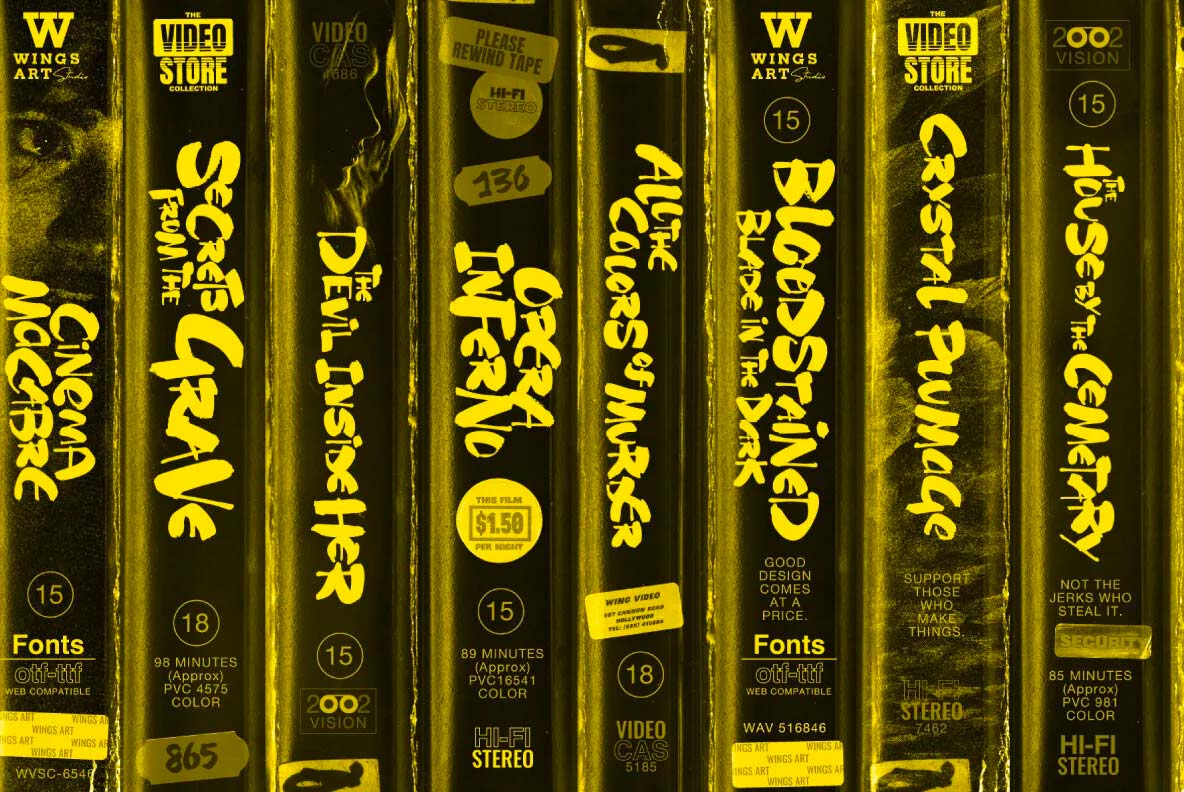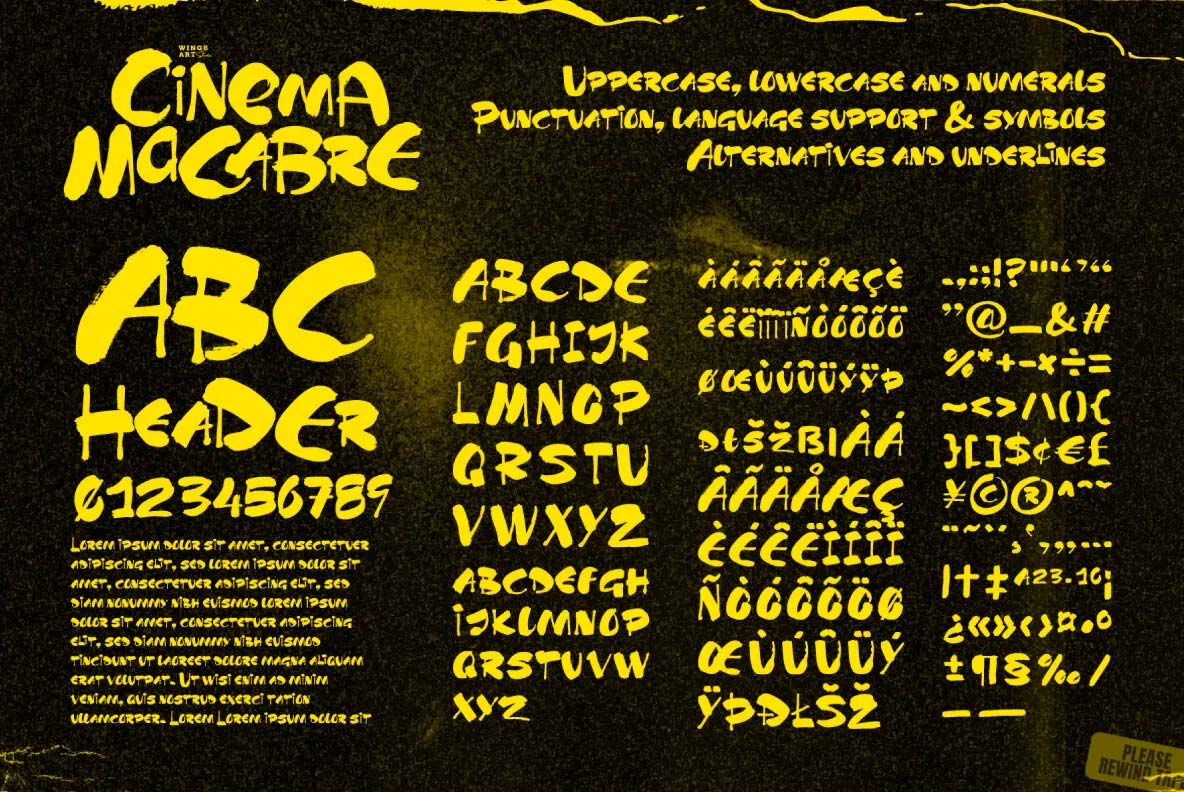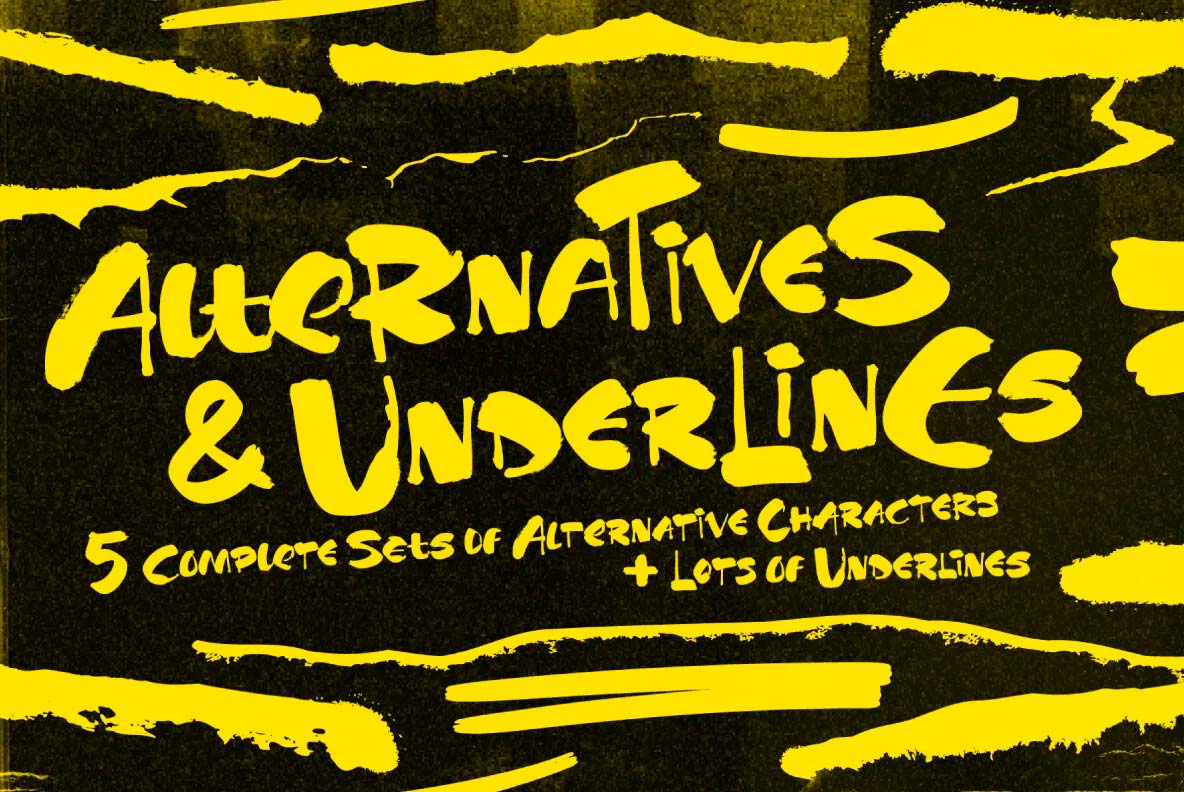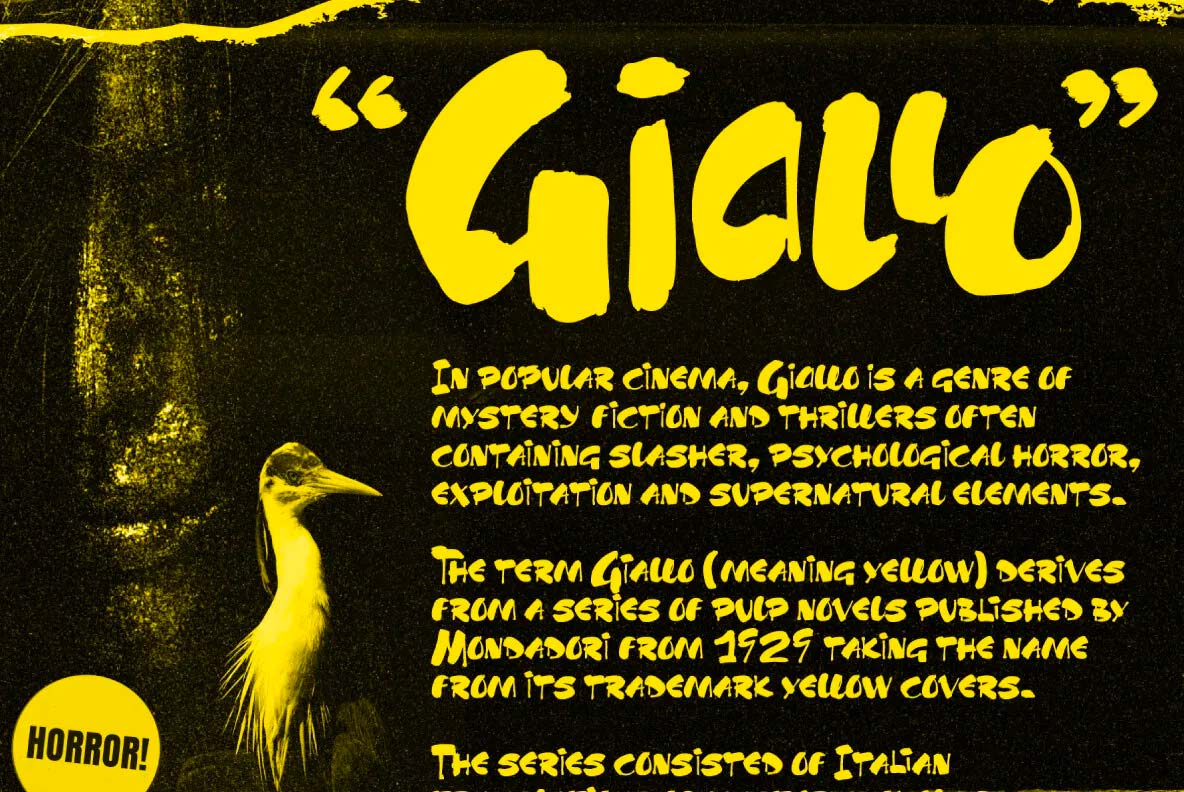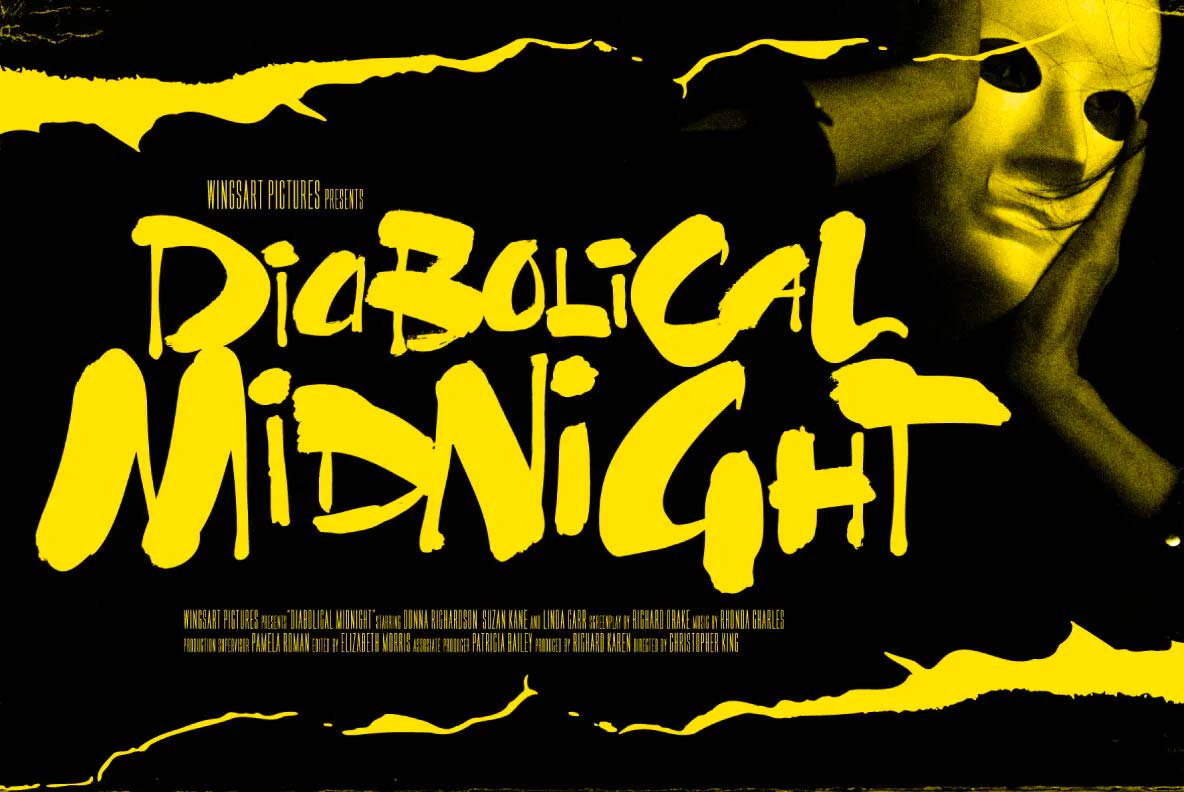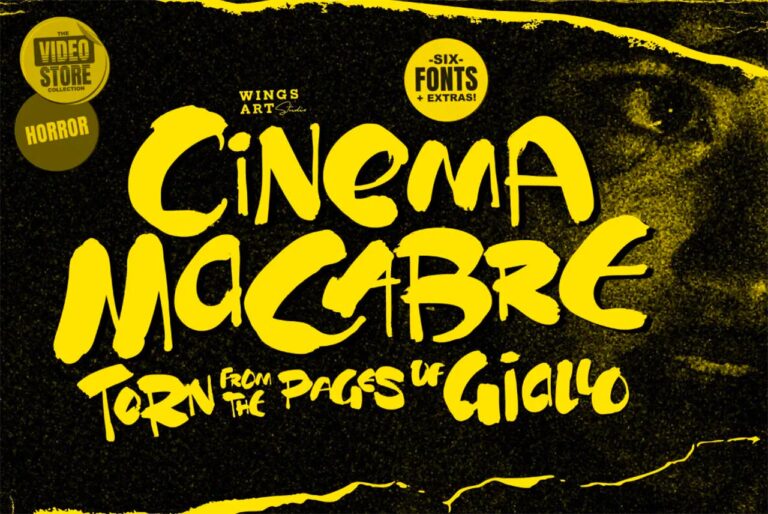
Cinema Macabre – Phông chữ hiển thị vẽ tay để tạo ra những tiêu đề ma quái nhất.
Phông chữ này được lấy cảm hứng từ các áp phích phim Giallo cổ điển những năm 1960 đến 1980 – một thể loại điện ảnh đình đám được yêu thích nhờ hình ảnh ấn tượng, nhạc phim đầy ám ảnh và hoạt động tiếp thị mang tính khai thác. Đây là một thiết kế được vẽ mang đến cảm giác ma quái nhằm nổi bật tính kinh dị, cổ điển trong khi vẫn linh hoạt đủ để sử dụng trên nhiều thiết kế kỹ thuật số khác nhau.
Bộ font Cinema Macabre bao gồm sáu kiểu chữ, mỗi kiểu chữ chứa một bộ ký tự chữ in hoa và chữ thường riêng biệt, cũng như số và hỗ trợ nhiều ngôn ngữ. Kèm theo đó là một loạt các kết hợp chữ đặc biệt, gạch chân và yếu tố đồ họa tùy chỉnh, tạo nên một bộ công cụ cần thiết để tạo ra thiết kế tiêu đề với dạng chữ kiểu như được làm thủ công.
Cinema Macabre là một kiểu chữ thường cho sự thử nghiệm bằng cách kết hợp các lựa chọn chữ in và chữ thường, với các kết hợp thú vị đang chờ được khám phá và truyền cảm hứng trên các áp phích của bạn, bài sách, album… Rất ít kiểu chữ khác cung cấp tính linh hoạt để tạo ra những thiết kế đầy ma quái như vậy!